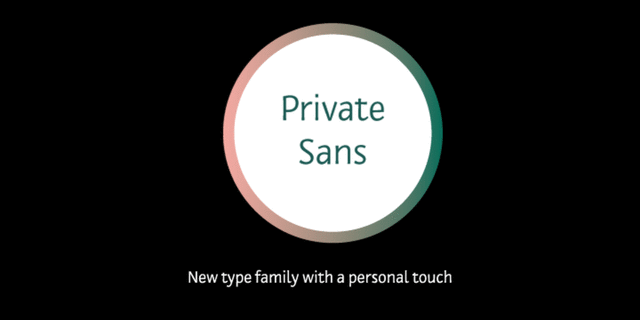
Шрифт Private Sans (Приват Санс) – это динамичный гуманистический гротеск, основанный на каллиграфическом письме широким пером. Он обладает подвижным живым характером, что нечасто можно видеть в текстовых кириллических шрифтах. Знаки имеют обратный энтазис, плавное окончание штрихов и наклон внутреннего овала. Название гарнитуры отражает намерение дизайнера спроектировать шрифт для личных посланий, где повествование ведется от первого лица. Предполагается, что он будет использоваться в блогах, электронной почте, персональных сайтах, т.е. там, где автор как бы ненадолго впускает читателя в свой мир, в свое личное пространство. Его также можно использовать для мемуаров, автобиографий, интервью, а также в литературных произведениях, посвященных мыслям, переживаниям и личным чувствам авторов. Private Sans – это шрифт для эмоциональных воспоминаний и разговоров по душам. Гарнитура спроектирована Ольгой Карпушиной в трех начертаниях и является развитием ее дипломного проекта на курсе «Шрифт и типографика» Британской высшей школы дизайна в Москве. Выпущена компанией ПараТайп в 2010 году.